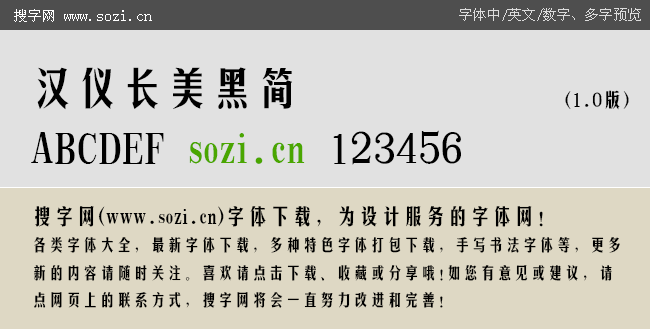
漢儀長(zhǎng)美黑簡(jiǎn)
搜字網(wǎng)提供一款漢儀長(zhǎng)美黑簡(jiǎn)中文字體下載,漢儀長(zhǎng)美黑簡(jiǎn)具有字體勻稱、清秀美觀的特點(diǎn),給人端正又正氣的視覺(jué)效果,,可適用于包裝印刷、廣告設(shè)計(jì)、平面設(shè)計(jì)、書(shū)籍報(bào)紙標(biāo)題應(yīng)用等領(lǐng)域。